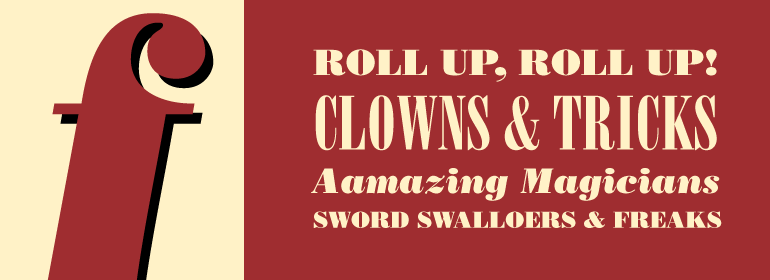
Bodoni Poster
尽管在字体设计上与印刷之王(Bodoni)几乎没有相似之处,但Poster Bodoni将现代字体的笔画对比功能推向了极致。它是由Chauncey H. Griffith于1929年设计的,风格酷似19世纪的宽大字体。在所有字重(Black、Black italic以及Compressed)中,细窄的字怀形状与坚固且赏心悦目的主笔画进行缓冲。巧妙细微的差别(例如Q的字尾以及圆形的末尾)使这种字体同时给人一种愉悦且印象深刻的感觉,非常适合广告和标识使用。”
Though it bears little resemblance to the types designed by the King of Printers (Bodoni) , Poster Bodoni pushes the stroke contrast feature of the modern faces to a captivating extreme. It was designed by Chauncey H. Griffith in 1929, and resembles the fat-faces of the nineteenth century. In all weights - black, black italic, and compressed - the skinny counter shapes are cushioned by solid and satisfying main strokes. Clever nuances (like the tail of the Q and the ball terminals) help to give this type a simultaneously cheerful and impressive ambiance that's great for advertising and signage."